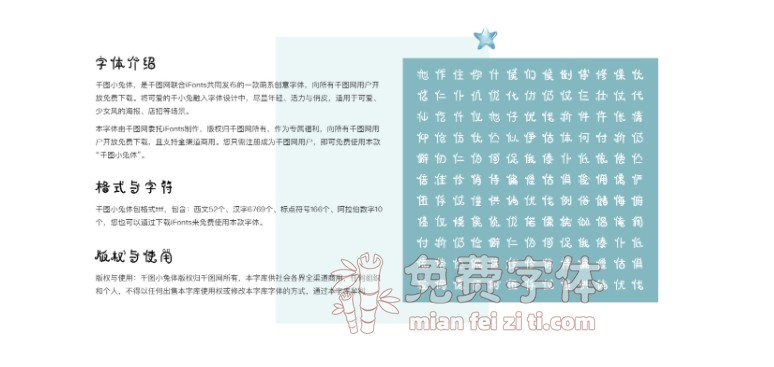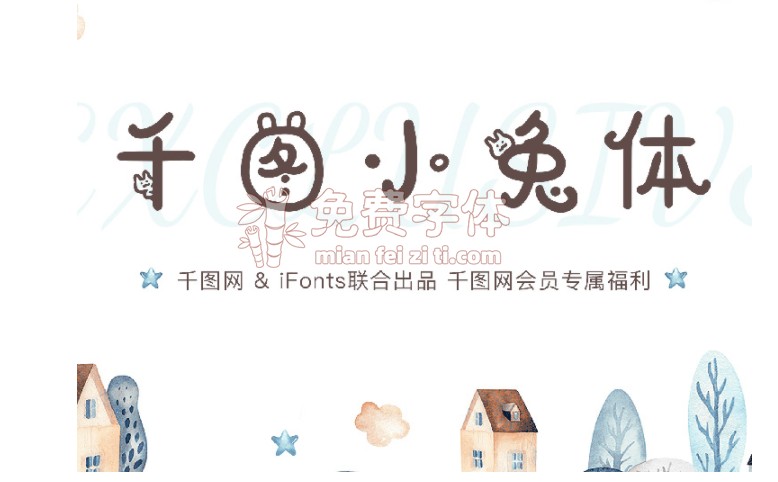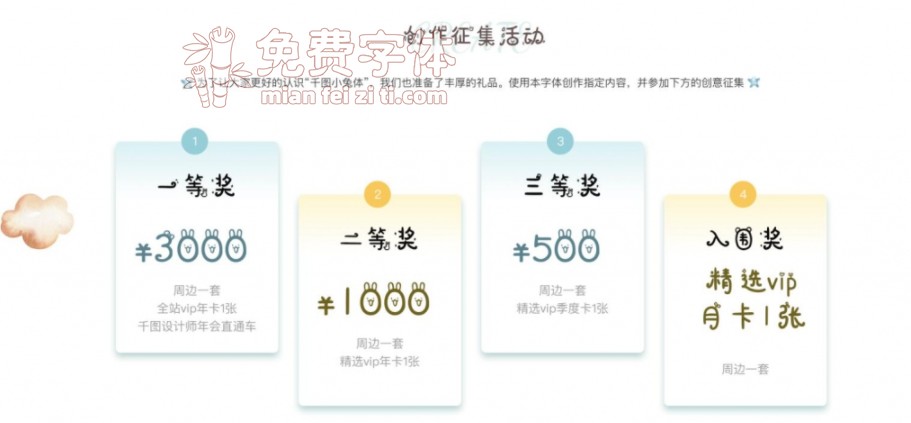
千图小兔体 | 千图网联合iFonts共同发布的一款萌系免费创意字体字体资讯
千图小兔体是千图网联合国内专业字体设计机构iFonts共同发布的一款萌系创意字体,历时半年多悉心打磨完成。向所有千图网用户开放免费下载。将可爱的千小兔融入字体设计中,尽显年轻、活力与俏皮,适用于可爱、少女风的海报、店招等场景。